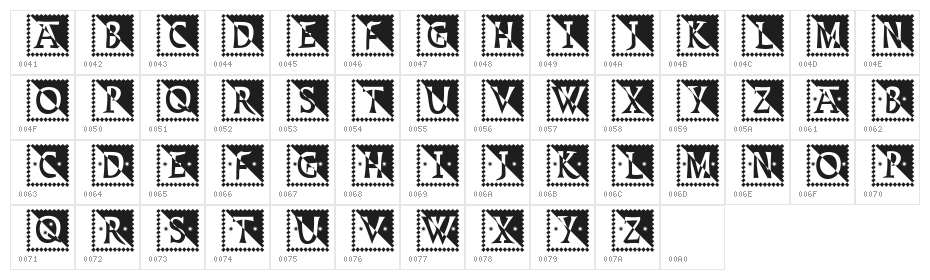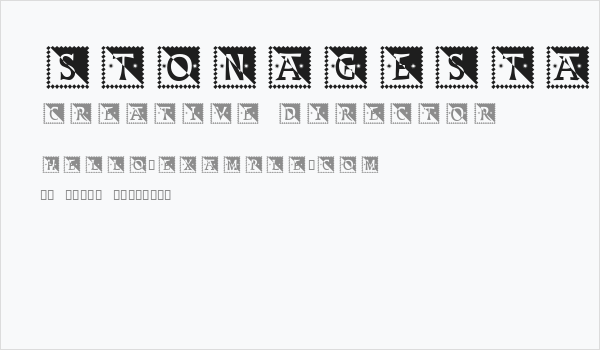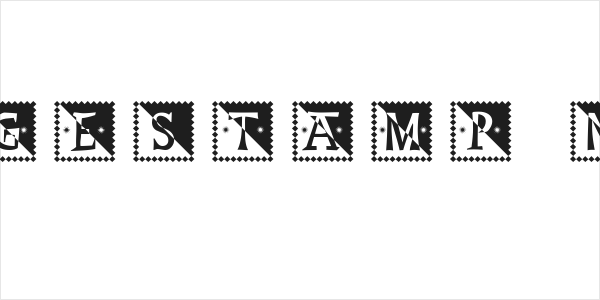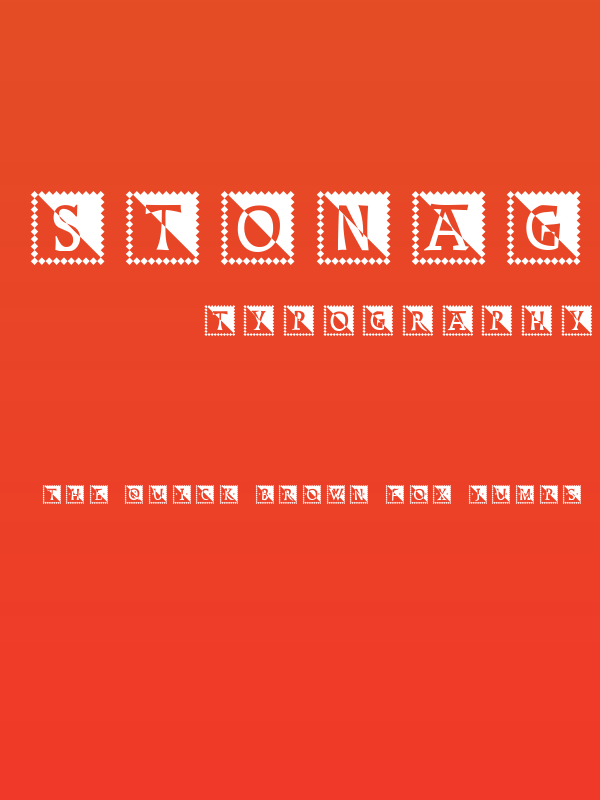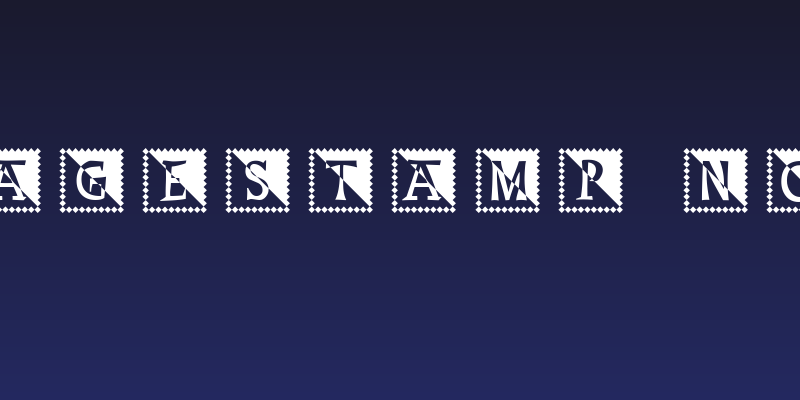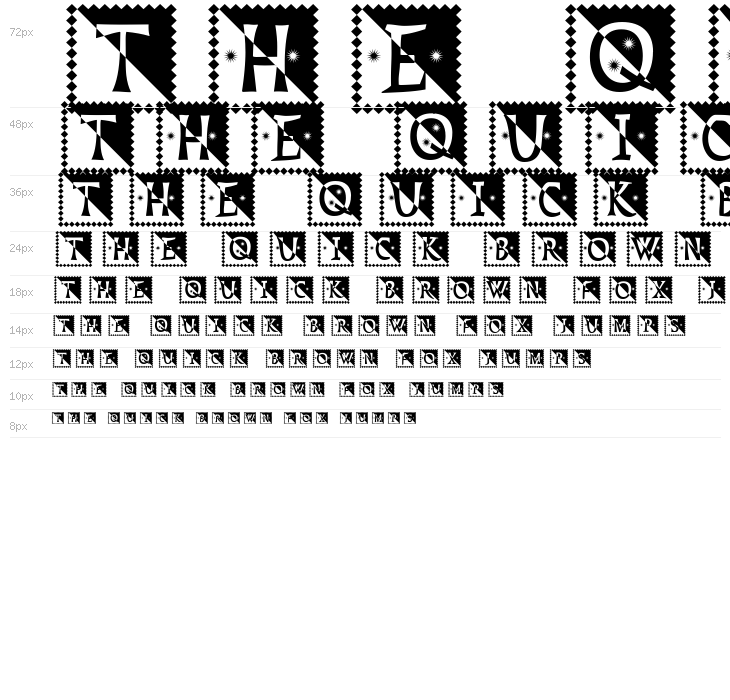
StonageStamp Normal Font
| Gesamtstil | Vintage |
| Anwendungsfall | Logos, Headlines, Posters |
| Vorgeschlagene Projekte | Ideal for vintage-themed designs, posters, greeting cards, and branding projects that require a distinctive and artistic touch. |